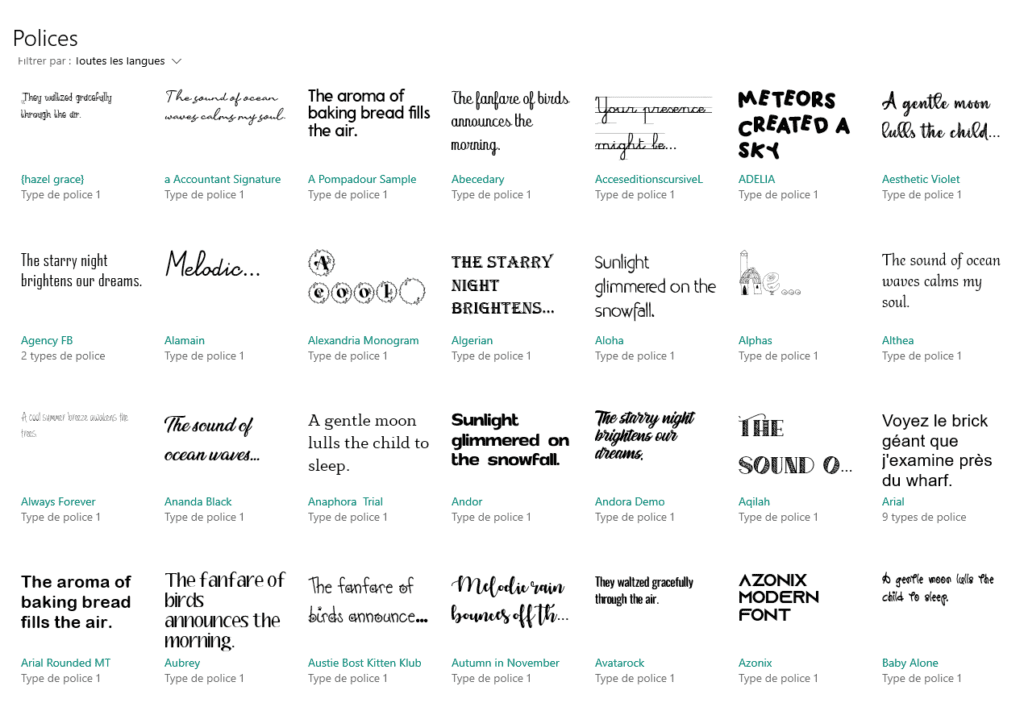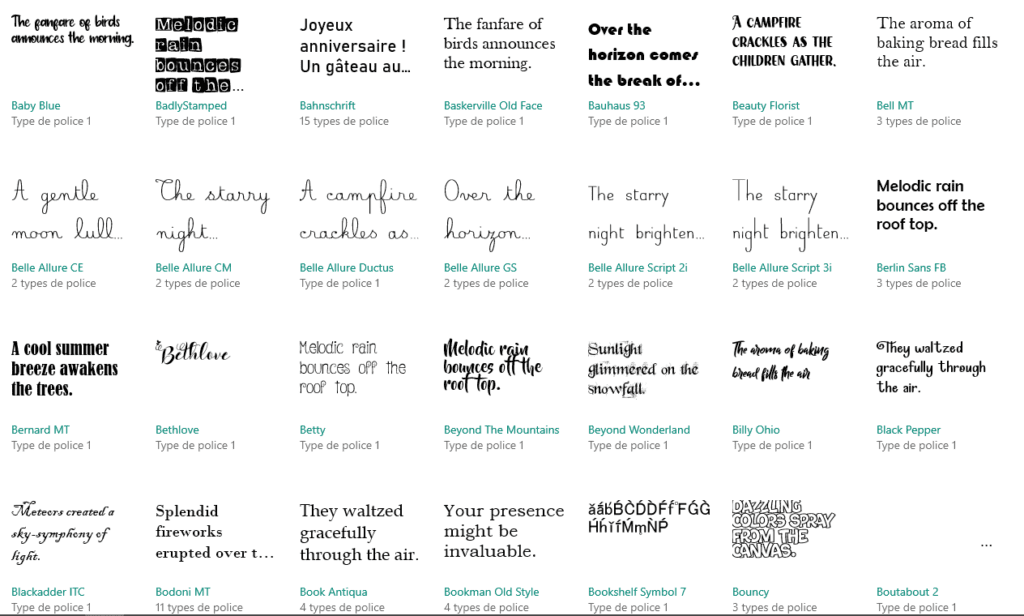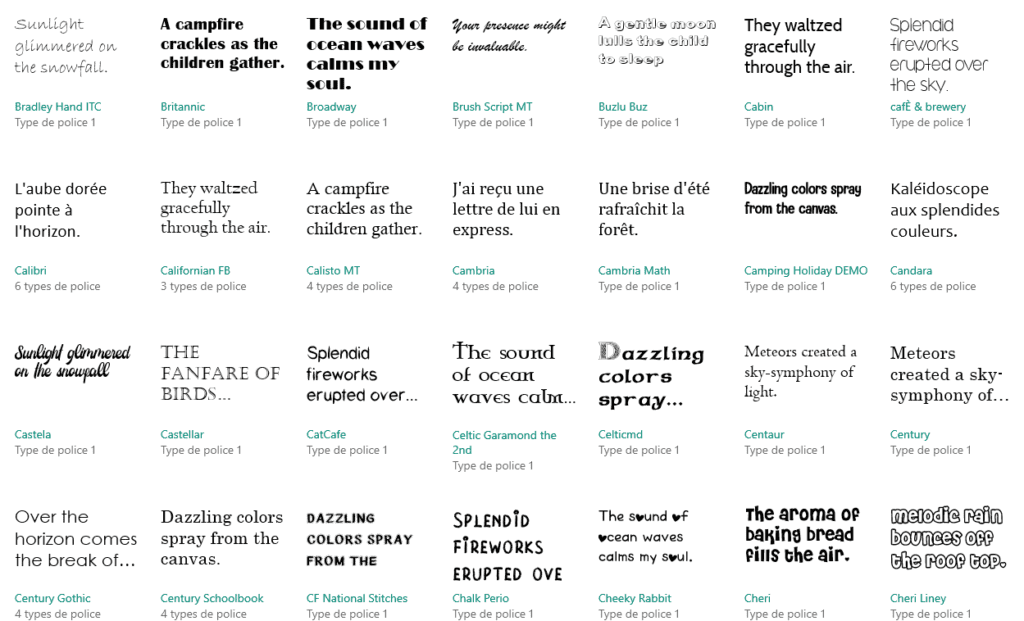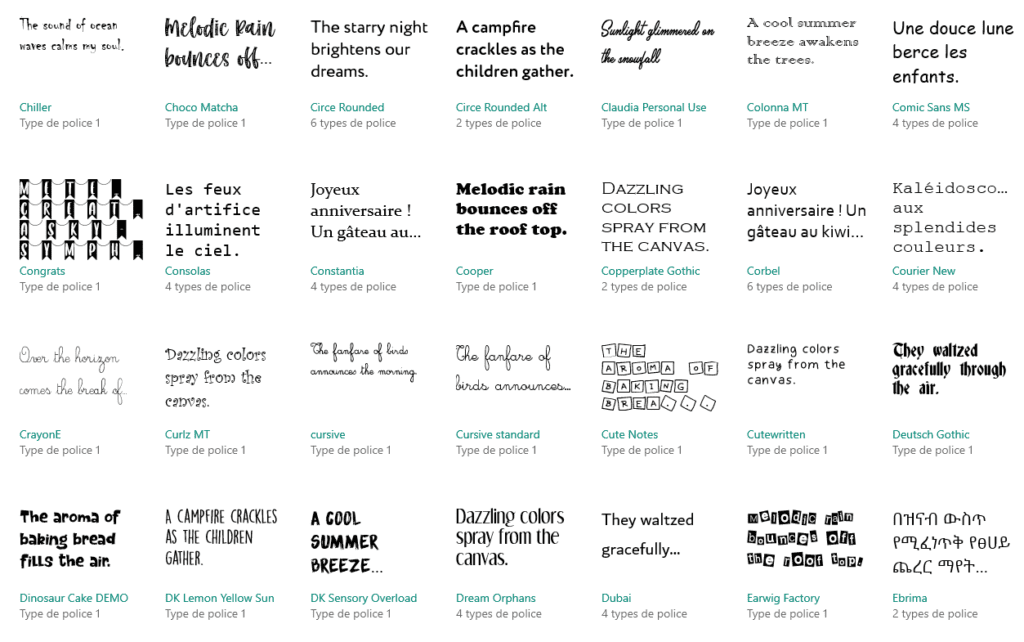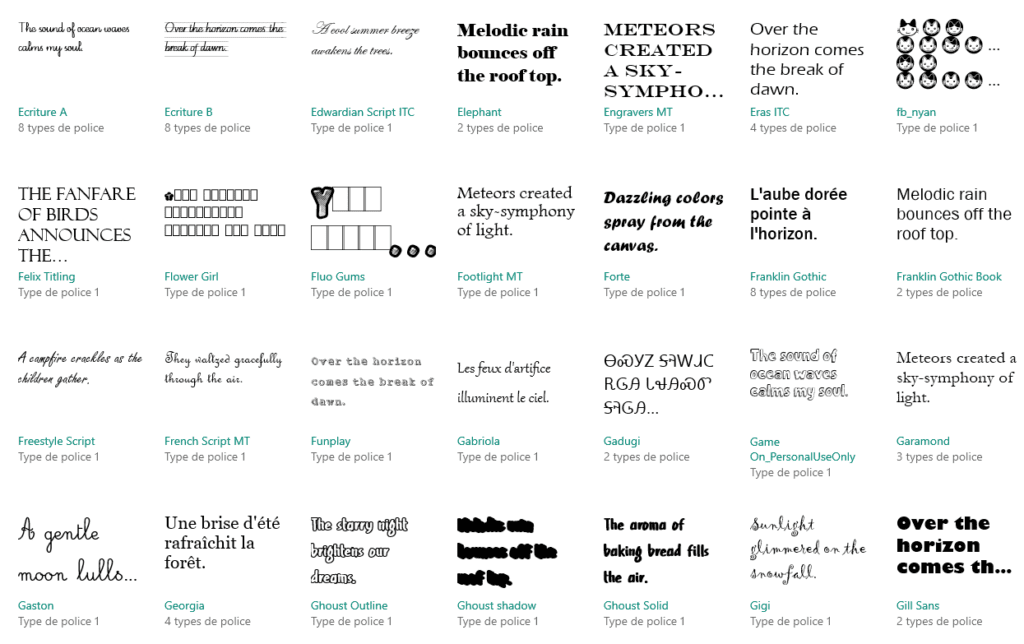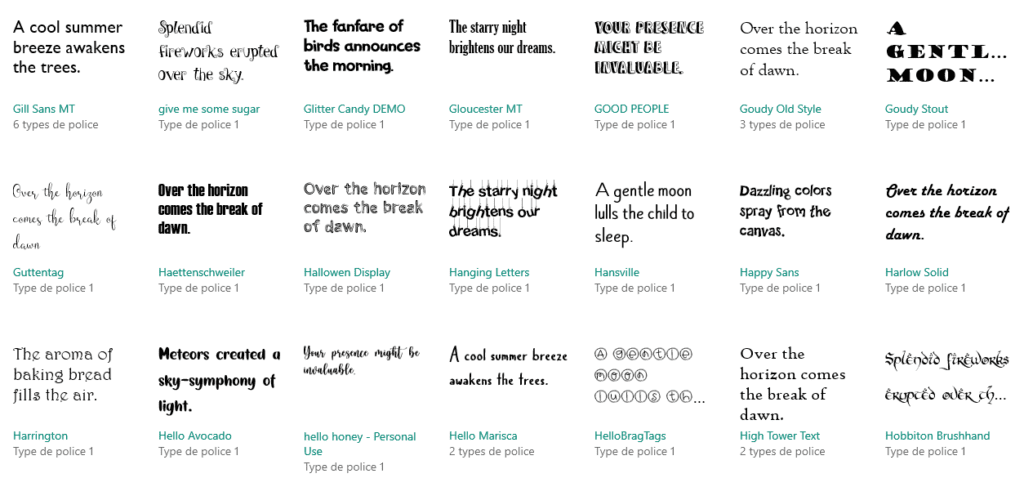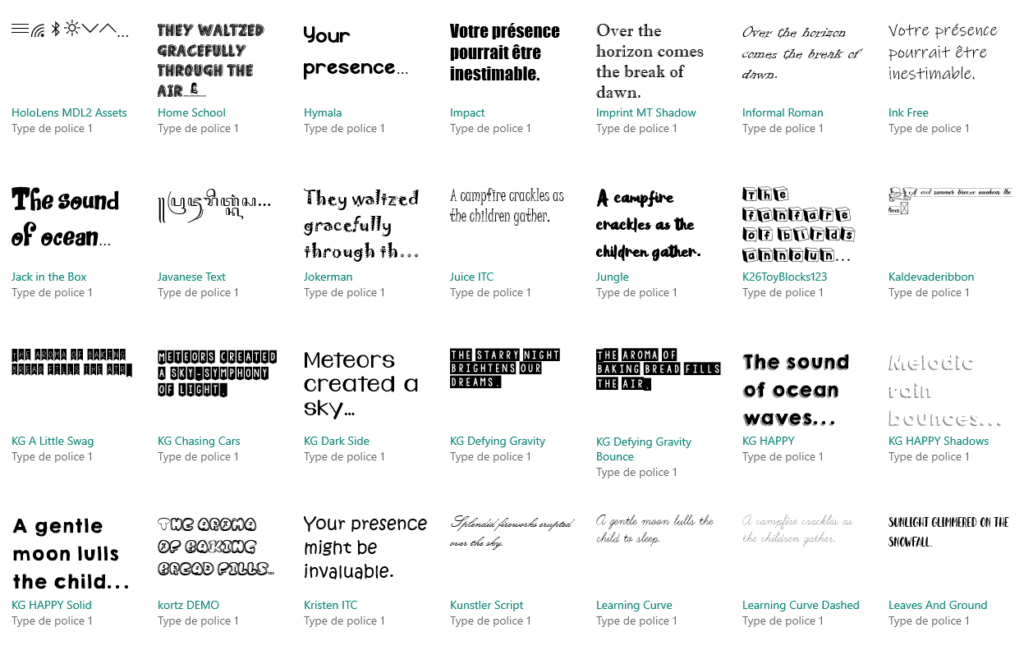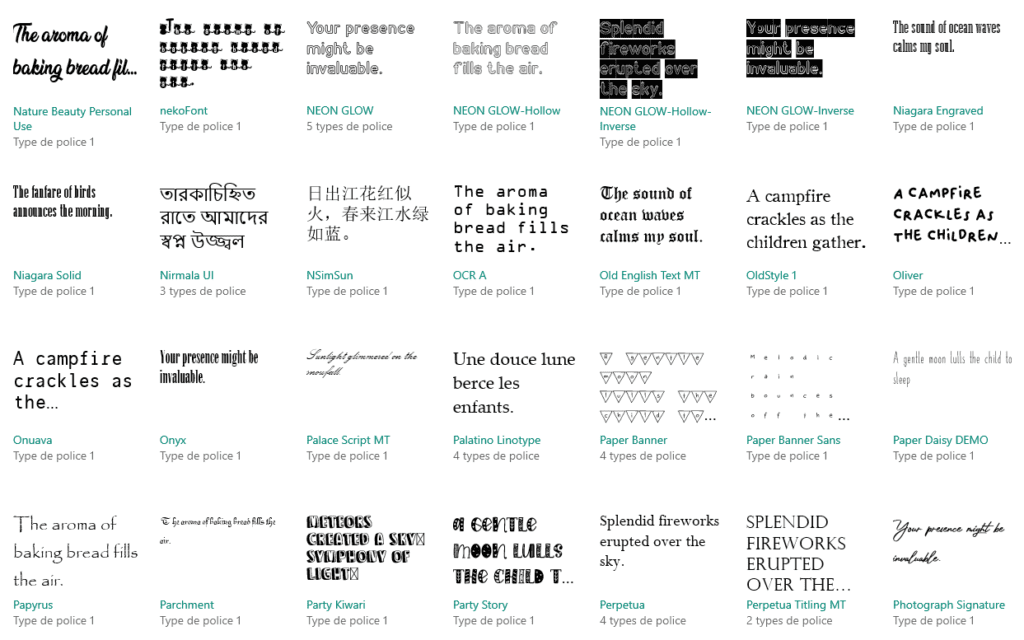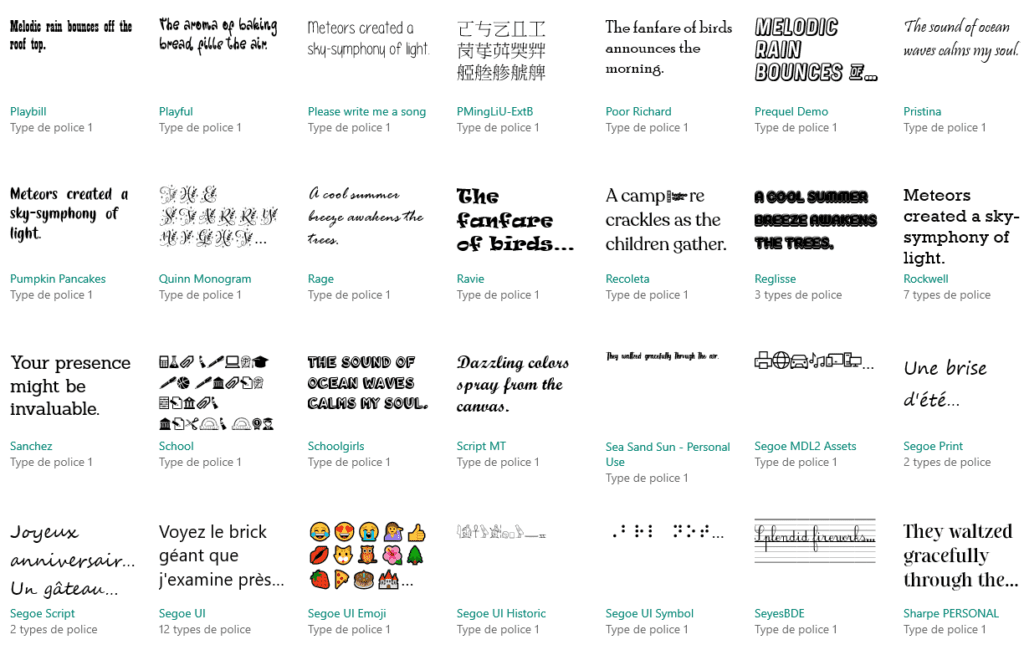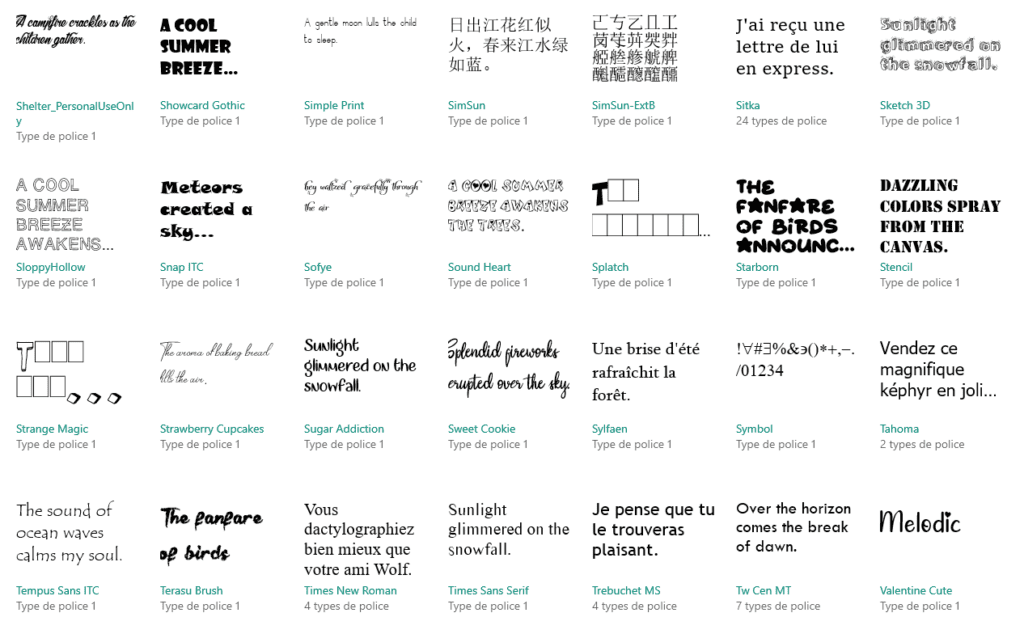
La liste de toutes les polices d’écriture disponibles sur votre PC
Dans les paramètres, vous pouvez visualiser toutes les polices d’écritures installées sur le PC. Il y a aussi les polices de base proposées par Windows, et que nous avons tous.
J’ai pensé que vous lister l’ensemble des polices d’écriture que j’utilisais pour la classe serait un peu inutile : j’en télécharge des nouvelles très régulièrement, mes goûts ne seront pas les vôtres et ce serait très fastidieux de tout noter !
Je vous propose tout de même de simples copies d’écran ci-dessous, qui vous permettent de voir rapidement les polices d’écriture que j’ai actuellement sur mon PC, et que j’utilise donc pour réaliser mes documents. 🙂
Petite parenthèse
La police Belle Allure, qui est à ma connaissance la meilleure police d’écriture gratuite en cursif, nécessite un petit coup de main pour fonctionner correctement.
Vous devez sélectionner votre texte sous Word, vous rendre dans les paramètres de police, puis cocher « Utiliser les variantes contextuelles » pour lier les lettres les unes avec les autres.